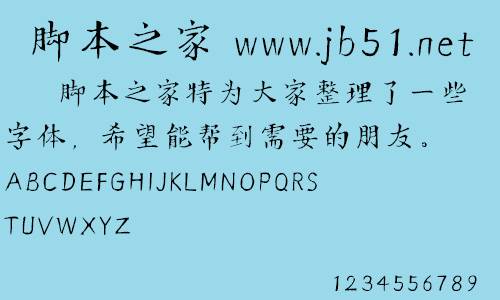
方正滕占敏竹刻简体
方正滕占敏竹刻体简体由方正字库出品的一款不错的艺术字体,字体笔触粗细适中,字体平正严谨,疏密有致,笔画中加入了斜切角,撇、捺笔画呈镜像对称。适合应用于艺术设计、平面宣传设计、网页设计,书法等领域。
刻字大师滕占敏以竹为纸,以刀为笔,在竹制笔杆上,创制独特竹刻体。此体以欧楷为本,结合各体所长,字体平正严谨,疏密有致,擅用竹子特性,笔锋转折处见刀锋犀利,横画破竹飞掠,竖画顺竹深入,笔意与刀法结合。竹刻体将中国传统竹刻技艺嫁接于现代科技,是对中华传统文化保护的一大创举。